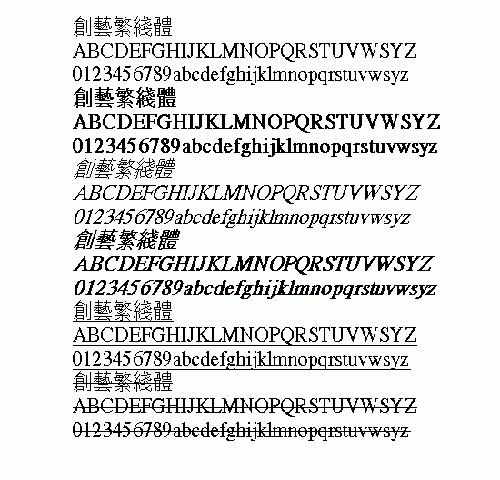
創(chuàng)藝繁線體是一款非常有個(gè)性的是創(chuàng)藝字體繁體類型,字體線條流暢繁體顯示彰顯個(gè)性,美工創(chuàng)作名片設(shè)計(jì)都非常常見(jiàn)??靵?lái)綠色資源網(wǎng)下載體驗(yàn)吧!
創(chuàng)藝繁線體是一款應(yīng)用于設(shè)計(jì)方而的繁體中文漢字,該字體端正大方得體,一筆一畫非常規(guī)則,整體效果十分出眾,可以應(yīng)用于平面設(shè)計(jì)、廣告設(shè)計(jì)、報(bào)紙雜志、正文標(biāo)題等領(lǐng)域,喜歡的網(wǎng)友可免費(fèi)下載收藏。